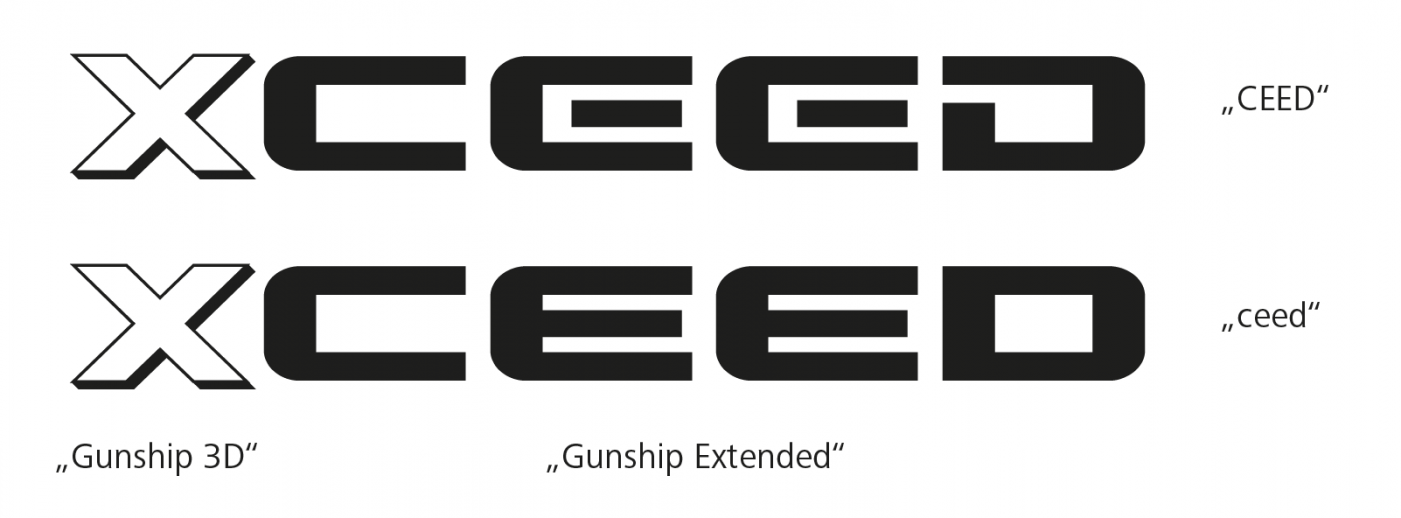
Suche eine ähnliche Schriftart (Kia XCEED)
KIA hat für den XCEED einen Schriftzug rausgebracht, der vom Design her sehr gut aussieht. Gibt es da eine Schriftart, die der von KIA ähnlich ist? Sie ist breit und fett, daher für mich sehr interessant. Besonders durch das Freihalten von Zwischenräumen wie beim "D" finde ich sehr gelungen. Gerade im Motorsport findet man häufig solche Schriften. Leider bin ich noch nicht fündig geworden. Wäre schön, wenn jemand diese Schriftart - oder eine ähnliche - kennt und mir hier weiterhelfen kann.
Schau Dir doch mal die Clan extended oder die Eurostile extended an, die gehen in die Richtung.
Danke, die Eurostyle kommt zwar schon von der Form hin, ist aber noch zu dünn gehalten. Ich suche solche Schrift, die ich dann auch vernünftig plotten kann.